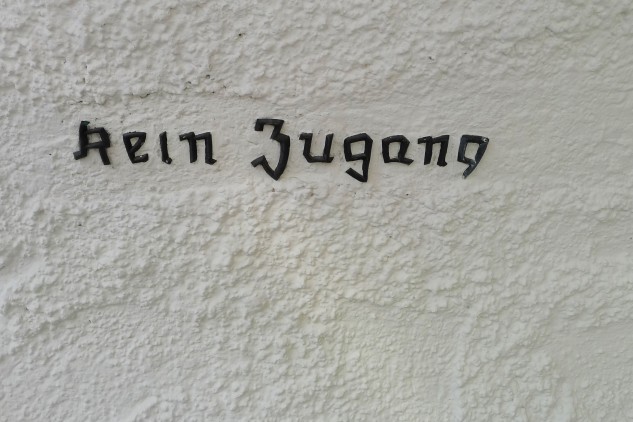
kein Zugang – Nordkettenbahn
Die Stationen der Nordkettenbahn wird 1927/28 von Franz Baumann im Stil der Tiroler Moderne erbaut. Die Beschriftung entwarf er – ebenso wie die die gesamte Innenausstattung und alle Möbel – selbst. Die eigenwilligen Metallbuchstaben wirken wie in die Wand "eingeputzt". Diese hier befinden sich an der Talstation Hungerburg. Sehr speziell und zum Glück unter Denkmalschutz.